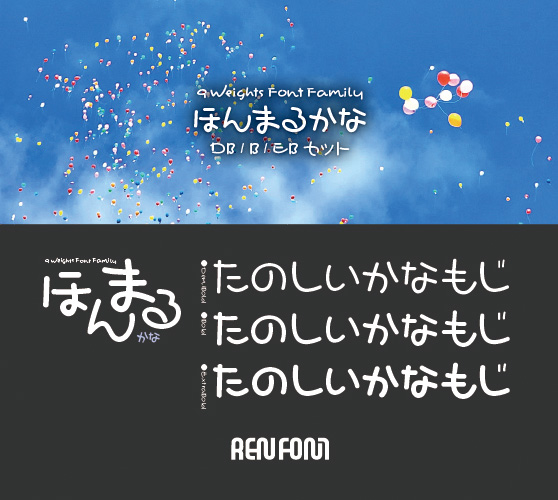
手書き風書体
ほんまるかな-中・小見出し用3ウェイトセット(DB/B/EB)
HommaruKana-DB,HommaruKana-EB
かすかに筆文字の名残り、味わいのある丸もじ。やや左上に重心がある独特のフォルム。既存の他社丸ゴシックと組み合わせても違和感なく溶け込み、あたたかな雰囲気を醸し出します。
縦組み・横組みのすべての文字にペアカーニングをほどこしており、メトリクス処理をするだけで、バランスのとれた組みが得られます。中・小見出し用3ウェイトセット。